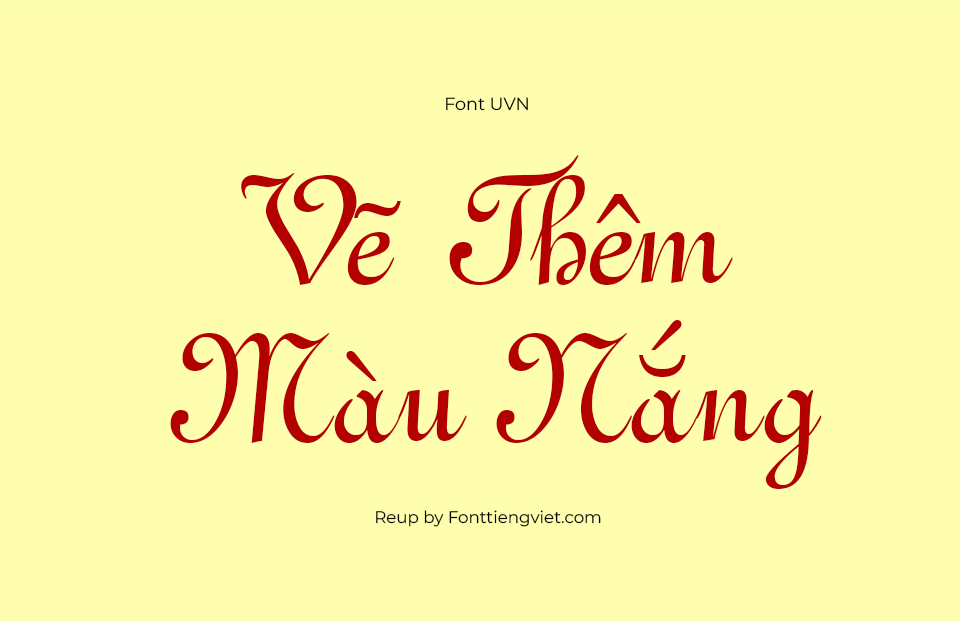
Font Việt Hóa UVN Con Thuy
Giới thiệu về Font Việt Hóa UVN Con Thuy
Trong thế giới thiết kế đồ họa, việc lựa chọn một Font Miễn Phí phù hợp là yếu tố then chốt để tạo nên sự ấn tượng. Font Việt Hóa UVN Con Thuy là một trong những bộ phông chữ độc đáo, mang đậm nét nghệ thuật truyền thống nhưng vẫn giữ được sự tinh tế hiện đại. Được phát triển bởi nhóm UVN, bộ chữ này đã được tối ưu hóa hoàn toàn để hiển thị tiếng Việt một cách mượt mà, không gặp lỗi dấu hay khoảng cách. Đây là lựa chọn lý tưởng cho những ai đang tìm kiếm sự khác biệt trong các dự án sáng tạo.
Đặc điểm nổi bật của phông chữ
Font Việt Hóa UVN Con Thuy sở hữu những đường nét thanh mảnh, uốn lượn mềm mại như dòng nước, đúng với tên gọi “Con Thuy”. Các nét chữ có độ dày vừa phải, tạo cảm giác dễ chịu cho người đọc nhưng vẫn đủ sức hút để làm nổi bật thông điệp. Phông chữ này cực kỳ phù hợp cho các em học sinh làm báo tường, giáo viên thiết kế bài giảng điện tử hoặc các nhà thiết kế thiệp chúc mừng, bìa sách nghệ thuật.
Ứng dụng thực tế của Font Việt Hóa UVN Con Thuy
Nhờ tính thẩm mỹ cao, Font Việt Hóa UVN Con Thuy được ứng dụng rộng rãi trong nhiều lĩnh vực khác nhau. Bạn có thể sử dụng nó để trang trí tiêu đề bài viết, tạo logo mang phong cách hoài cổ hoặc thiết kế các ấn phẩm truyền thông văn hóa. Khả năng tương thích tốt trên nhiều phần mềm đồ họa như Photoshop, Illustrator giúp người dùng dễ dàng thao tác và sáng tạo không giới hạn.
Lưu ý khi sử dụng bộ font này
Dù là một phông chữ đẹp, bạn nên kết hợp Font Việt Hóa UVN Con Thuy với các font không chân đơn giản để tạo sự cân bằng cho bản thiết kế. Tránh dùng quá nhiều chữ in hoa liên tục để đảm bảo tính thẩm mỹ cao nhất.
Kết luận về bộ font nghệ thuật